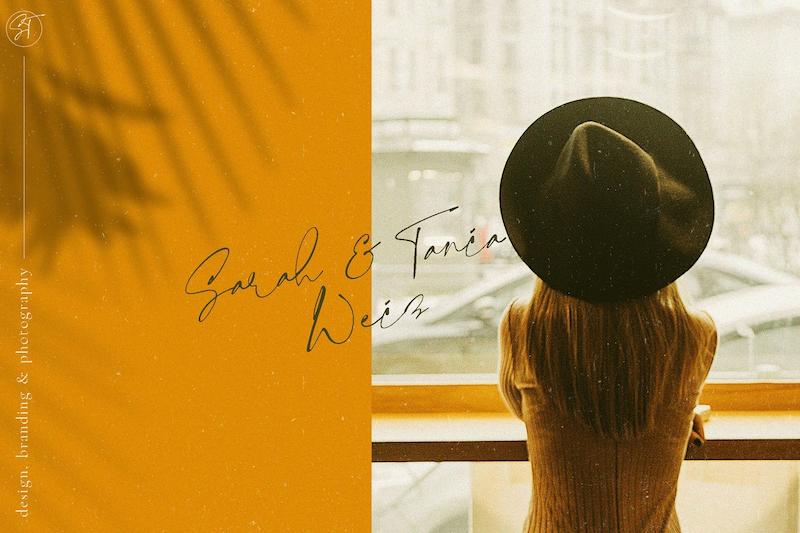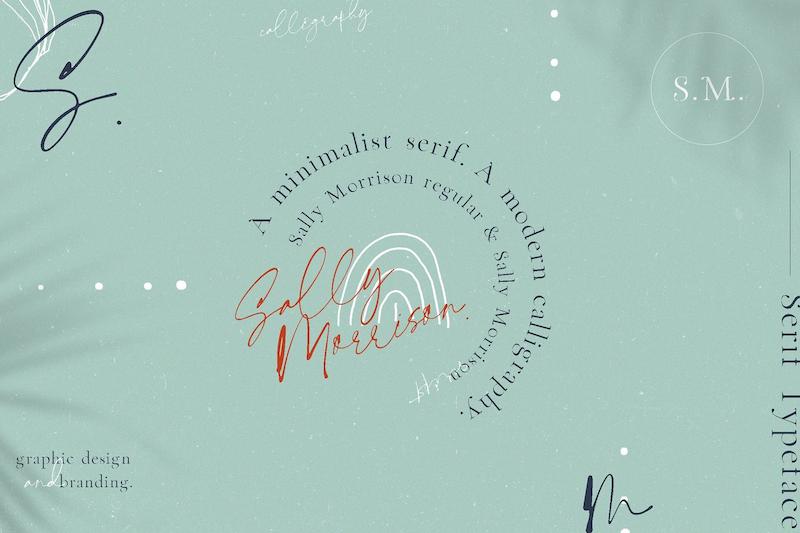
فونت انگلیسی دوگانه شیک و چشم‌نواز فمینین (Sally Morrison)
معرفی فونت سالی موریسن
سالی موریسون، یک فونت دوگانه مدرن است، ترکیبی از خوشنویسی شیک و فونت سِریف مینیمالیستی. با لیگاتورهای منحصربه‌فرد، سالی موریسون فونتی عالی برای وبلاگ، لوگو، شبکه‌های اجتماعی، برندسازی، پوستر، نقل‌قول‌ها، کارت‌های عروسی و موارد دیگر است، شما تصمیم می‌گیرید! این فونت شامل کاراکترهای دارای اکسنت برای زبان‌های بین‌المللی نیز می‌باشد (برای مشاهده گلیف‌های موجود به تصاویر پیش‌نمایش مراجعه کنید) و 54 لیگچر منحصربه‌فرد در سالی موریسون اسکریپت.
ویژگی‌های سالی موریسون:
• فونت دوگانه: اسکریپت و سِریف
• سبک قلم نازک
• دستخط نچرال و مدرن
• گلیف‌های دارای اکسنت برای کاربرد چندزبانه
• 52 لیگچر منحصربه‌فرد
• طبقه‌بندی: سریف، اسکریپت
• فاصله‌گذاری: نرمال
• اندازه بهینه: هر اندازه‌ای